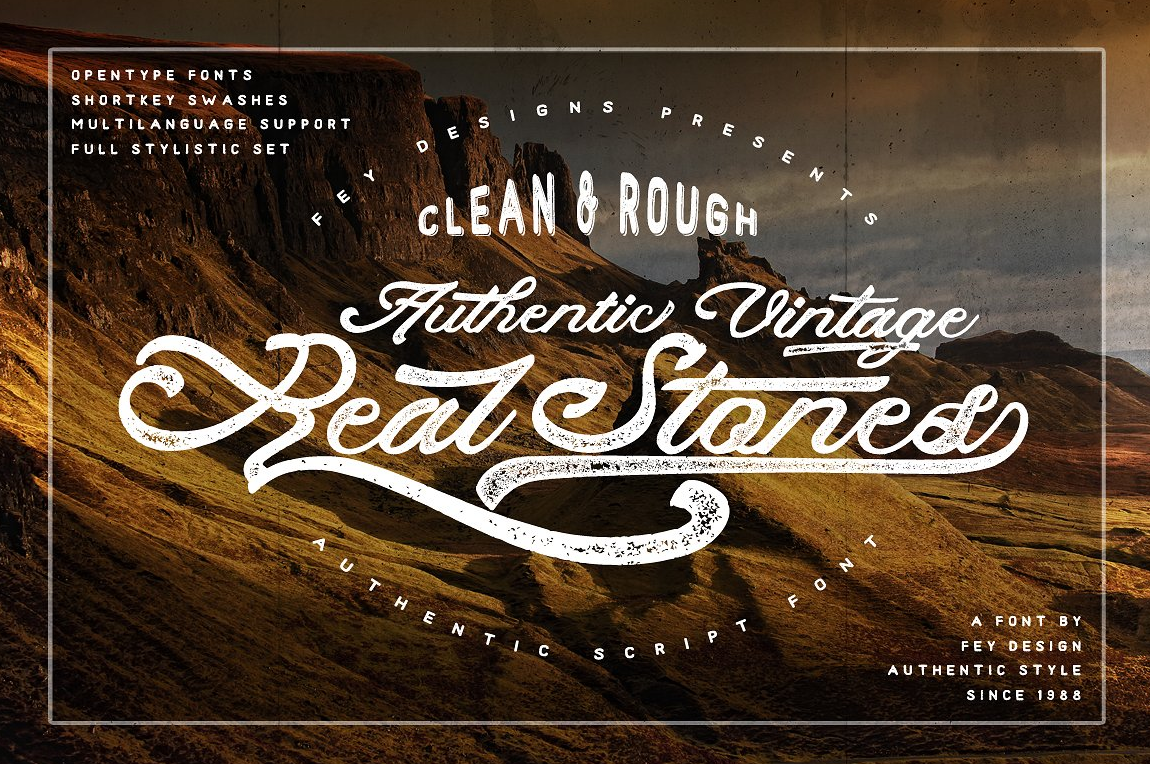
Real Stones Script Font
Introduzimos a Real Stones Script Font! Desenhada por Feydesign, esta é uma fonte premium disponível no Creativemarket. Recentemente, a Feydesign lançou esse belo estilo de escrita chinesa gratuita para download. A Real Stones – Clean And Rough apresenta um sabor autêntico do estilo da escrita chinesa com duas opções: limpo e grosso. É perfeitamente adaptável para projetos diversos, como design, elementos digitais, festas, eventos, camisetas, logotipos, medalhas, adesivos ou qualquer outro trabalho de arte incrível. Neste formato elegante e autêntico da escrita chinesa, você encontra o que está procurando para personalizar seus projetos de maneira única e profissional.